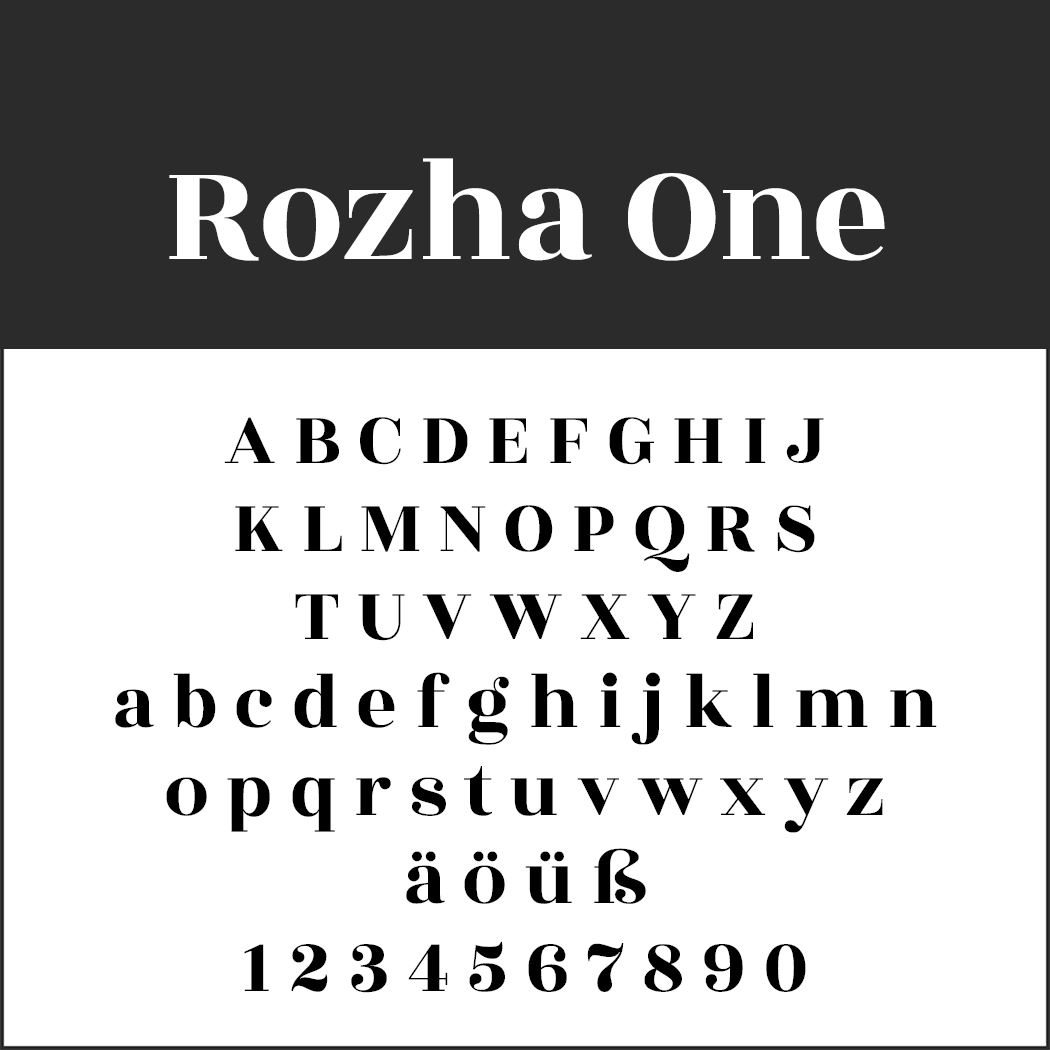
In der Weihnachtszeit darf in jeder Hinsicht etwas dicker aufgetragen werden: beim Text, bei der Bildauswahl und bei der Typografie. Was sonst als geschmacklos gelten würde, ist zum Fest der Liebe nicht nur erlaubt, sondern meistens sogar goldrichtig. Das gilt ganz besonders für weihnachtliche Schriftarten.
Wer es dennoch in der besinnlichen Zeit nicht so kitschig möchte, wählt alles einen Ton nüchterner. Dass das trotzdem weihnachtlich wirken kann, beweist unsere stimmungsvolle Sammlung an kostenlosen Fonts. Hier ist für jeden Geschmack eine weihnachtliche Schriftart dabei.
Schriftarten mit weihnachtlichen Motiven
Eine weihnachtliche Schriftart darf ruhig gleich als solche zu erkennen sein. Diverse Symbole sorgen dafür, dass kein Zweifel daran besteht, zu welchem Fest hier Grußkarten, Einladungen und Briefe verschickt werden.
Mit den Fonts lassen sich aber nicht nur Weihnachtskarten gestalten, auch für andere Zwecke sind diese geeignet. Nutzen Sie die Schriftarten beispielsweise auch für Überschriften auf Plakaten oder Flyer. So lassen sich Angebote in der Weihnachtszeit festlich in Szene setzen. Auch als Weihnachtswunsch auf Geschenkanhängern oder Geschenkpapier machen sich die Schriften gut.
Schriftart Hello Christmas
Der Name ist Programm: Christbaumkugeln, Weihnachtsbäume, Geschenke und Glocken in den Großbuchstaben ergänzen die mit starkem Hauptstrich geführte geschwungene Schrift.
Schriftart Christbaumkugeln
Dieser Font ist ein guter Kompromiss für alle, die es nicht so kitschig mögen, aber trotzdem nicht auf weihnachtliche Symbolik verzichten wollen. Die Kugeln wirken sachlich, die Vintage-Buchstaben lockern die strenge Anordnung etwas auf.
Weihnachtliche Schriftarten mit Schneesymbolen
Auch wenn bei diesen winterlichen Fonts nicht explizit mit Weihnachtsaccessoires gearbeitet wird, verbindet man Schnee doch meistens mit dem Fest der Liebe, so dass der Bezug für alle klar wird.
Schriftart Kingthings Christmas 2
Wie aus einem alten Märchenbuch gefallen und mit Schneeflocken verziert: So wirkt dieser Font, der ganz ohne eindeutige Symbolik sehr weihnachtlich auftritt.
Schriftart Cartoon Blocks Christmas
Als hätte man die Buchstaben einfach in den Schnee gesteckt, auf dass frische Flocken darauf fallen: Diese Cartoon-Schrift eignet sich besonders für junge und dynamische Branchen.
Weihnachtliche Schriftarten mit einem Funken Nostalgie
Diese Fonts besitzen zwar nicht per se einen weihnachtlichen Charakter, vermitteln aber ein heimeliges Gefühl und wirken, z. B. ergänzt durch entsprechende Symbole wie Glocken oder Stechpalmzweige, sehr festlich.
Schriftart MelindaMelinda
Geschwungen und verschnörkelt lenkt Melinda die Blicke auf sich, kommt sowohl für das obligatorische „Frohe Weihnachten“ als auch etwas längere Begleittexte infrage.
Schriftart Rozha One
Der kontrastreiche Font orientiert sich an typischen Plakatschriften des 19. Jahrhunderts und macht sich insbesondere bei einer hohen Schriftgröße gut.
Schriftart Typey McTypeface
Dieser Font verbindet Anleihen von alten Schriften mit erfrischend modernen Details. Besonders feierlich wirkt er im kursiven Schriftschnitt.
Schriftart Metro Retro NF
Eine Art-Deco-Perle von 1927 hat Nick Curtis mit diesem Font wiederbelebt. Was damals modern war, ist heute Retro – und nach wie vor schön. Weihnachtlich wird es mit entsprechender Farbgebung wie beispielsweise Dunkelgrün mit Bordeauxrot.
Festliche Dauerbrenner